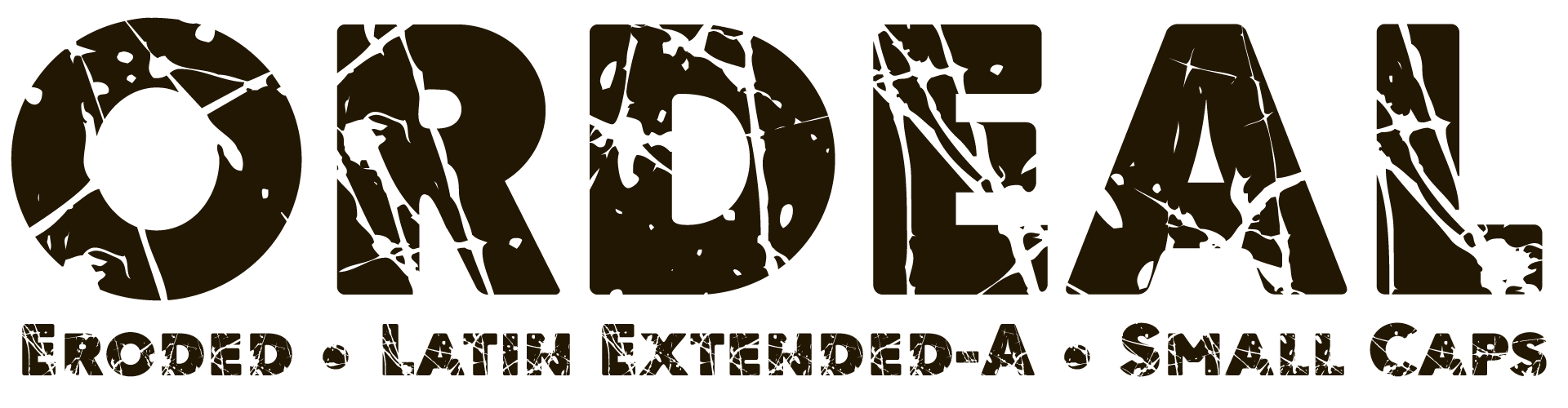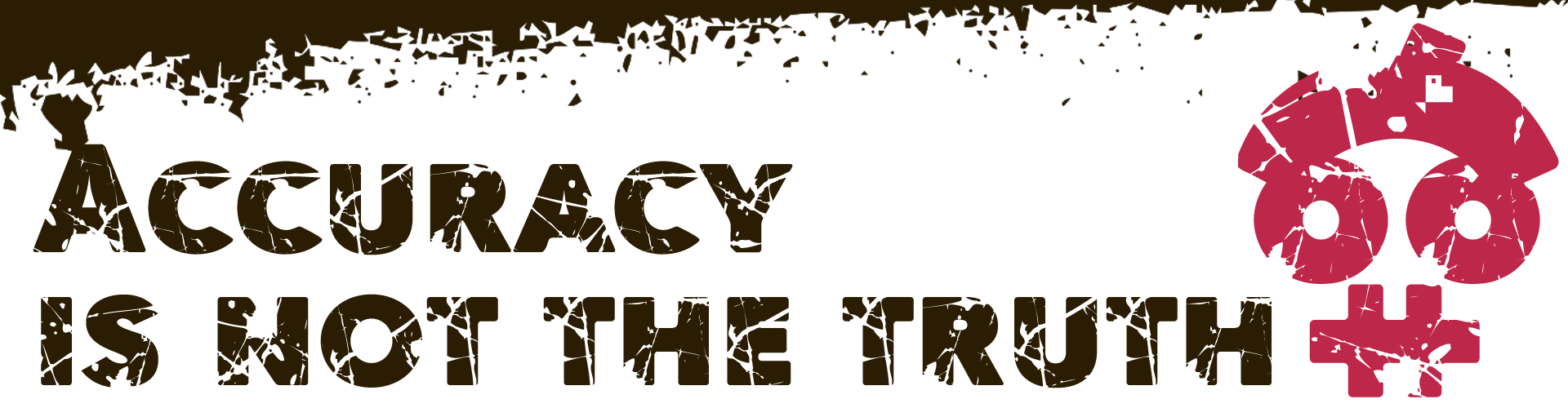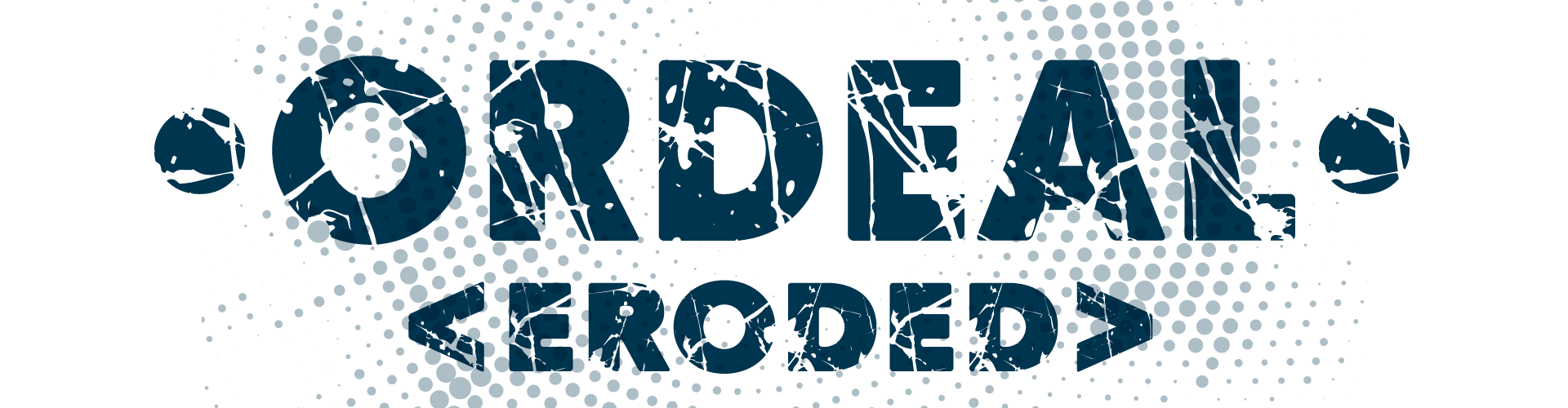
I Put My Hand On The Fire
Estilo: Sans Serif, Eroded, Grunge
Proporción: Black
Glyphs: 425
Año de publicación: 2018.
Funciones OpenType: Additional languages, All Alternates, Bitcoin, Capital Spacing, Contextual Alternates, Discretionary Ligatures, Kerning, Localized Forms, Optical Size, Ordinals, Small Capitals, Standard Ligatures.
Con soporte completo para todos los idiomas derivados del Latín y funciones OpenType esta fuente es una solución versátil para cualquier diseño publicitario o de marca donde se tenga la intención de plasmar un aspecto único y genuino.
La tipografía Ordeal Eroded dispone en su versión comercial de un juego de 425 glifos (Latin Extended-A) con versalitas y soporte para cualquier idioma europeo o centro europeo derivados del Latín. Ordeal Eroded también incluye funciones OpenType (Compatibles con InDesign, QuarkXpress, Photoshop e Illustrator.